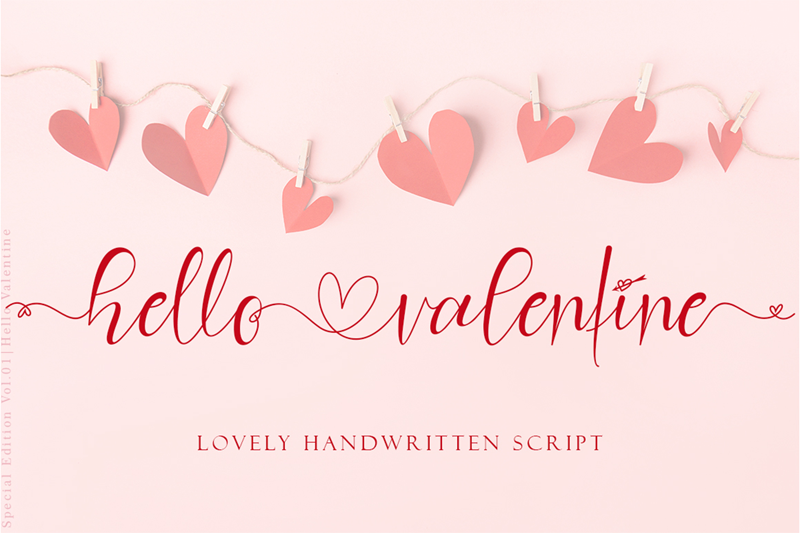
Font Hello Valentine font Nét Chữ Lãng Mạn Cho Thiết Kế Đầy Cảm Xúc
Giới Thiệu Về Font Hello Valentine
Font chữ là một yếu tố quan trọng trong thiết kế, giúp truyền tải thông điệp và cảm xúc. Hello Valentine là một font chữ độc đáo, mang phong cách lãng mạn, ngọt ngào, thích hợp cho các thiết kế liên quan đến tình yêu, ngày lễ Valentine, thiệp cưới, hay các dự án sáng tạo đầy cảm xúc.
Với nét chữ mềm mại, uốn lượn và điểm nhấn hình trái tim, Hello Valentine giúp tạo nên sự thu hút và ấn tượng ngay từ cái nhìn đầu tiên. Bài viết này sẽ khám phá chi tiết về đặc điểm, ứng dụng và cách tải font Hello Valentine để sử dụng trong thiết kế.
Font Hello Valentine font Nét Chữ Lãng Mạn Cho Thiết Kế Đầy Cảm Xúc
Đặc Điểm Nổi Bật Của Font Hello Valentine
1. Phong Cách Lãng Mạn, Dễ Thương
Hello Valentine sở hữu nét chữ handwriting (viết tay) với các đường nét uốn cong mềm mại, tạo cảm giác gần gũi và ấm áp. Một số ký tự được cách điệu với hình trái tim, giúp tăng thêm sự ngọt ngào và phù hợp với chủ đề tình yêu.
2. Đa Dạng Kiểu Chữ
Font Hello Valentine thường có 2-3 kiểu chữ (Regular, Bold, Italic), giúp người dùng linh hoạt trong việc kết hợp để tạo điểm nhấn.
3. Hỗ Trợ Nhiều Ngôn Ngữ
Font này thường hỗ trợ bảng mã Unicode, bao gồm các ký tự tiếng Anh, tiếng Việt (có dấu) và một số ký tự đặc biệt, phù hợp cho nhiều dự án đa ngôn ngữ.
4. Dễ Đọc, Phù Hợp Nhiều Thiết Kế
Dù mang phong cách nghệ thuật, Hello Valentine vẫn đảm bảo tính dễ đọc, thích hợp cho:
• Thiệp Valentine
• Poster tình yêu
• Thiệp cưới, lời chúc
• Logo thương hiệu ngọt ngào
• Social media design
Ứng Dụng Của Font Hello Valentine Trong Thiết Kế
1. Thiệp Valentine & Quà Tặng
Với nét chữ lãng mạn, Hello Valentine là lựa chọn hoàn hảo để thiết kế:
• Thiệp Valentine handmade
• Sticker, decal dán kèm quà
• Ly sứ, túi vải in dòng chữ ngọt ngào
2. Thiết Kế Wedding & Anniversary
Font này cũng rất được ưa chuộng trong:
• Thiệp cưới
• Backdrop tiệc kỷ niệm
• Quà tặng cho đối tác, người thân
3. Social Media & Marketing
Các thương hiệu về mỹ phẩm, hoa tươi, quà tặng có thể sử dụng Hello Valentine để:
• Thiết kế banner Valentine
• Post Facebook, Instagram với thông điệp ngọt ngào
• Video lyric nhạc tình
4. In Ấn & Đồ Handmade
• Sổ tay, journal
• Tranh treo tường
• Áo thun, túi tote in chữ cách điệu
Lưu Ý Khi Sử Dụng Font Hello Valentine
• Kết hợp màu sắc phù hợp: Nên dùng tông màu hồng, đỏ, tím pastel để tăng tính lãng mạn.
• Không dùng cho văn bản dài: Vì là font nghệ thuật, nên hạn chế dùng cho nội dung nhiều chữ.
Kết Luận
Font Hello Valentine là một lựa chọn tuyệt vời cho các thiết kế liên quan đến tình yêu, sự ngọt ngào và lãng mạn. Với nét chữ độc đáo và linh hoạt, font này sẽ giúp sáng tạo của bạn trở nên ấn tượng hơn. Hãy tải ngay và bắt đầu thiết kế những sản phẩm đầy cảm xúc với Hello Valentine!